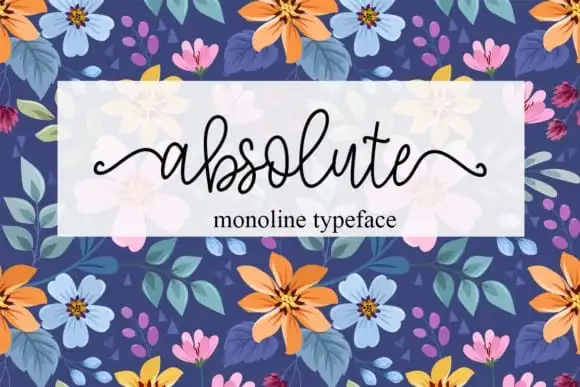
Absolute Handwritten Font – Download Grátis
A Absolute Handwritten Font é uma excelente escolha para aqueles que buscam uma fonte elegante e romântica para seus projetos de design. Criada com um toque de romantismo, essa fonte cuidadosamente desenvolvida combina a elegantura eterna da escrita à autêntica caligrafia. O resultado é uma harmonia entre simplicidade e sofisticação, perfeitamente adequada para aplicação em eventos especiais como convites de casamento ou cartões de agradecimento, mensagens pessoais como as cores de despedida, identificação visual de empresas e até mesmo elementos de marca personalizados. A sua elegância é tanto para os detalhes finos dos caracteres minúsculos quanto para o estilo fluido e suave dos conjuntos de letras completas. A Absolute Handwritten Font torna seu trabalho em design mais impecável, dando um toque único e autêntico que certamente impressionará seus clientes ou público-alvo.